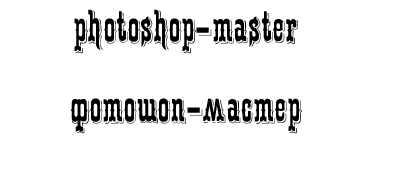
Шрифт - Patience
Интересный шрифт, который хорошо подходит для работы в фотошопе. Есть поддержка русского языка.
Внешний вид:
еее сразу вспоминаю игру Red dead redeption
Очень красивый шрифт!!!
Стильно)
ковбои ожили!!!!!!!сенкс)))))